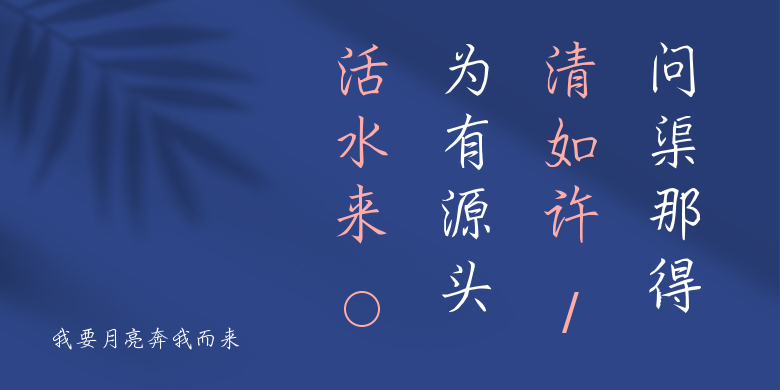
我要月亮奔我而来
我要月亮奔我而来,这款字体结构工整、笔画清晰,兼顾美观与易读性,适用于标题、正文、海报、包装、LOGO 等多种场景。字形优雅稳定,风格百搭耐看,适配日常排版与创意设计,让文字呈现更舒适、更具质感。我要月亮奔我而来一笔一画,皆是细节,以均衡的比例、流畅的线条打造舒适视觉体验,字形端正大气,风格简约现代。无论是商业设计、品牌宣传还是日常排版,都能轻松驾驭,让文字更有格调与力量。我要月亮奔我而来字体下载。